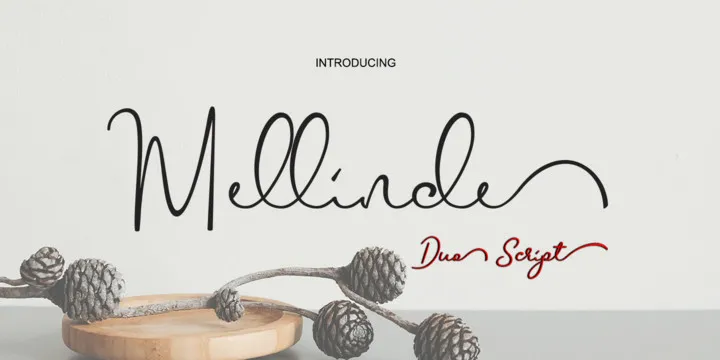
Mellinde Handwritten Font – Download Grátis
Descubra a autêntica mão que criou Mellinde Handwritten Font, uma fonte script ideal para pequenos negócios. Fundada com olhos e mãos atentos aos detalhes, Mellinde é um estilo de letra moderno e fresco, embora carregue uma leve nostalgia através da sua escrita artesanal. Essa fonte traz detalhes decorativos e linhas dançantes que são ideais para criar cartões de convite, material de marca, cartões de visita, citações e outdoors. Com um design que combina a elegância do handwritten com o frescor da atualidade, Mellinde é perfeitamente adaptável a diversos usos, desde cartões de agradecimento até materiais de publicidade, cartão de visita ou qualquer outro elemento visual que deseje dar vida aos seus projetos. Essa fonte não apenas oferece um toque único e elegante, mas também ajuda a transmitir um tom pessoal e autêntico para seus materiais promocionais, tornando cada peça única e memorável.